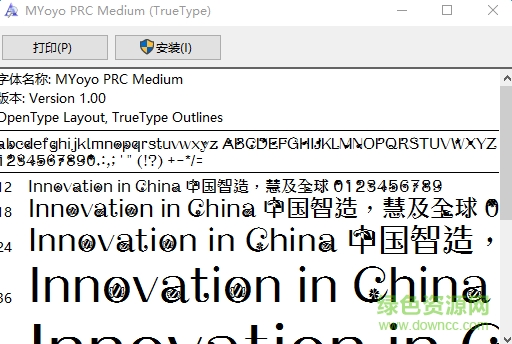
落葉歸根字體是一款很有特色的電腦藝術(shù)字體,寫(xiě)出來(lái)的字是很好看的,而且還有樹(shù)葉的裝飾,是不是很新奇呢,可以用于很多方面,喜歡這款字體的朋友可以隨時(shí)來(lái)綠色資源網(wǎng)下載。
落葉歸根字體是一款很不錯(cuò)的電腦字體,寫(xiě)出來(lái)的字極美,用于藝術(shù)設(shè)計(jì)、廣告設(shè)計(jì)等方面是很合適的,歡迎大家來(lái)綠色資源網(wǎng)下載。